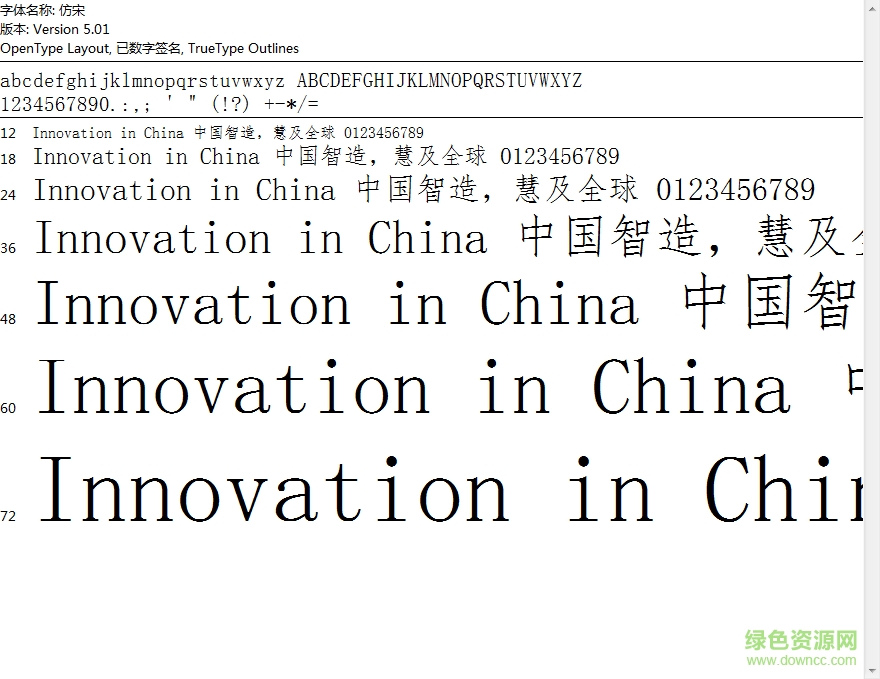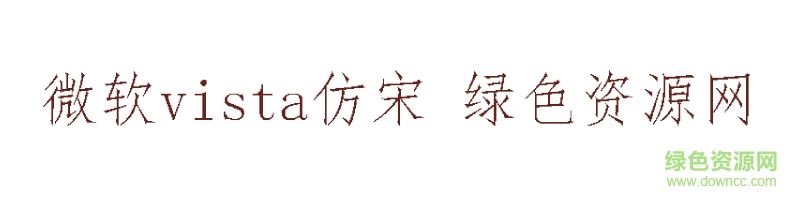
微軟vista仿宋是專為win系統(tǒng)提供的一款簡體字體,該字體端莊大氣,字型為標(biāo)準(zhǔn)的仿宋字體,具有簡淡秀潤、靈動瀟灑、簡遠(yuǎn)平和等特色,綠色資源網(wǎng)提供最全最新的中英文字體素材,歡迎下載使用!
微軟vista仿宋是印刷字體的一種,仿照宋版書上所刻的字體,筆畫粗細(xì)均勻,粗細(xì)一致、秀麗狹長,適用于樣本畫冊,報紙排版,網(wǎng)頁設(shè)計等廣告設(shè)計應(yīng)用。